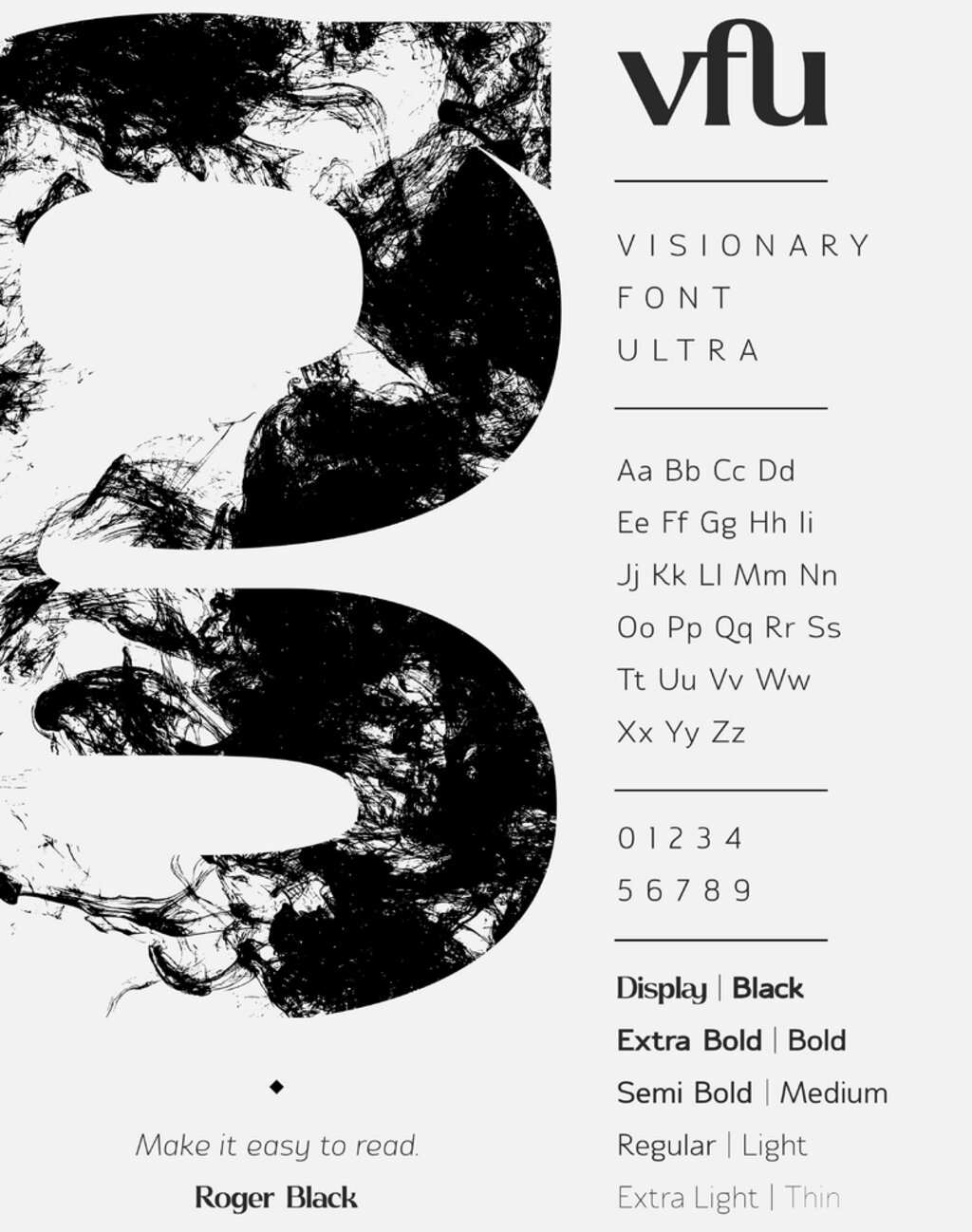
Студент на Варненския свободен университет /ВСУ/ представя оригинален шрифт на Международното триенале на типографията в Полша.
Шрифтът е наречен VFU (Visionary Font Ultra) и е изработен от студента от трети курс в специалност "Графичен дизайн" Володимир Федотов. Той е един от тримата представители на България, избрани за участие в изложбата на форума по типография "Проф. Юзеф Мрошчак". Творбите му ще бъдат изложени наред с плакати на млади автори от Полша, Дания, Германия, Великобритания, Франция, Нидерландия, САЩ, Аржентина, Япония, Китай. Изложбата, в която ще бъдат представени 50-те най-добри участници в конкурсната програма на Международното триенале на типографията, ще бъде открита на 21 март в Музея на печата в полския град Нови Тарг.
"За създаването на един шрифт е нужно усещане за симетрия, баланс и малко познания по математика, за да се спазват пропорциите във всяка буква.", обяснява Федотов. Казва, че пише проектите си в университета на собствени шрифтове, тъй като се гордее с тях.
Федотов очаква GOOGLE да вкара неговите шрифтове в своята база.